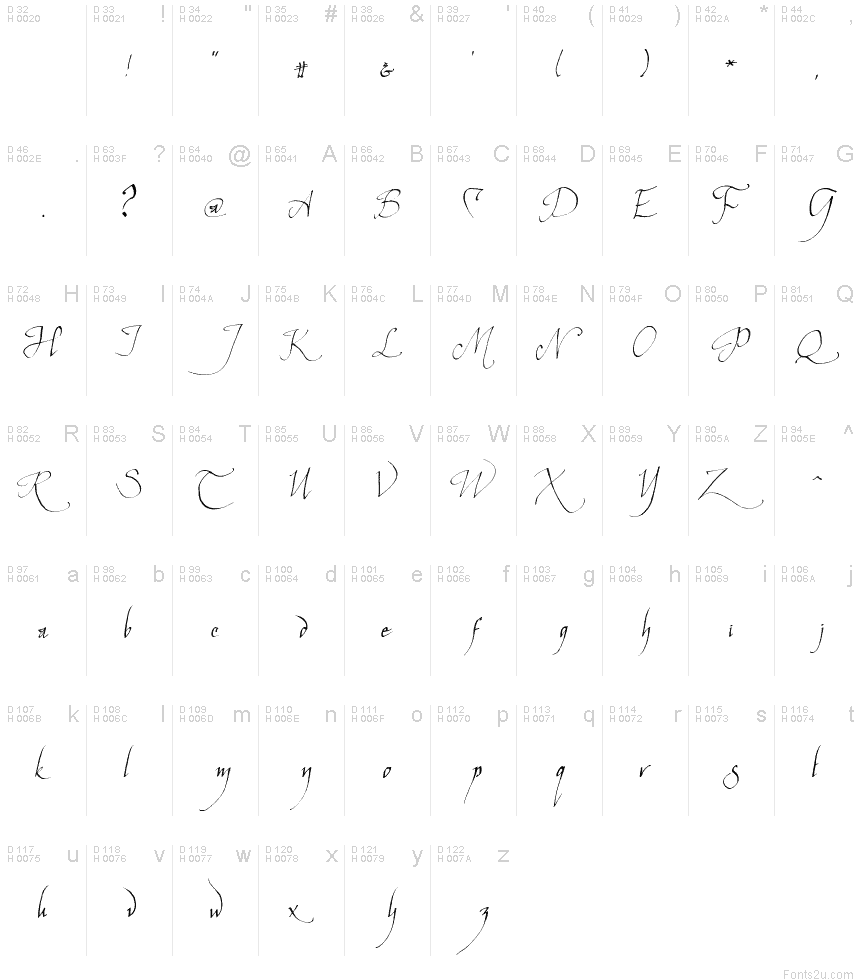
Elven Common Speak to darmowy krój kaligraficzny z cieniutkimi jak ostrza liniami i długimi, księżycowymi zawijasami, które wyglądają jak wyryte, a nie wydrukowane. Jego rytm jest lekki i nieco nieokiełznany, nadając słowom aurę dawnej magii, a przy tym pozostając czytelnym.
Elven Common Speak świetnie sprawdza się na okładkach książek fantasy, w tytułach kampanii RPG, na zaproszeniach do D&D, w menu gier, podpisach na mapach, etykietach mikstur czy świec oraz na plakatach z bogatą fabułą. Stosuj go w większym rozmiarze i zapewnij mu sporo światła, aby delikatne linie pozostały wyraźne; w tekście głównym połącz go z prostym krojem bezszeryfowym, takim jak Helvetica, lub subtelnym szeryfem, aby ten darmowy font mógł w pełni opowiedzieć swoją historię.